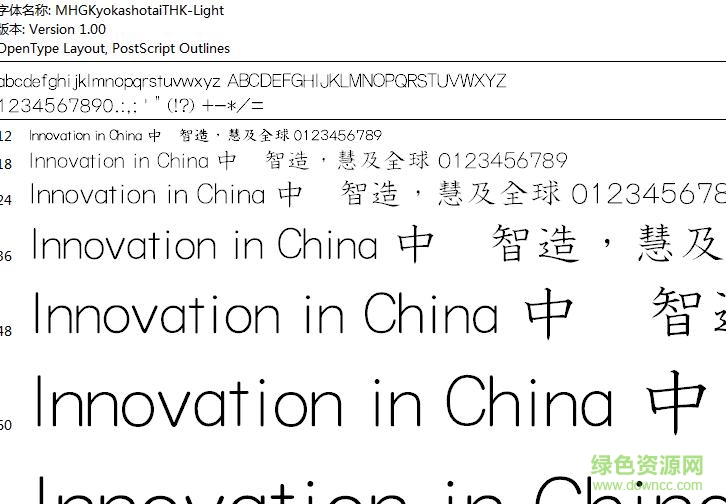
蒙納教科書體
蒙納繁和教科書體ttf是一款非常有特色的繁體字體,基于中國(guó)古代印刷字體宋體衍生而來,延續(xù)了字形端正、剛勁有力的特點(diǎn),喜歡這款字體的朋友歡迎下載使用!
蒙納繁和教科書體ttf簡(jiǎn)介
蒙納繁和教科書體是蒙納根據(jù)日本教科書字體打造的繁體中文字體,字形清晰,棱角分明,筆挺端莊獨(dú)具美感,整體效果出眾,可適用于廣告設(shè)計(jì)、平面設(shè)計(jì)、印刷包裝等領(lǐng)域!